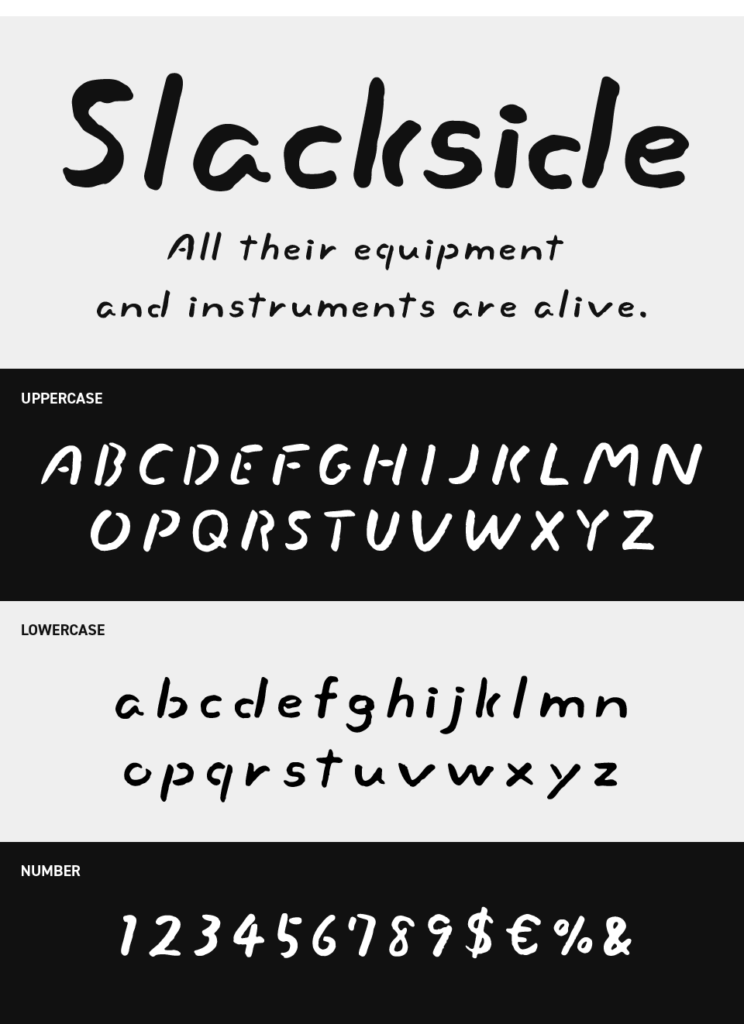
Slackside Font
Slacksideフォントは、ラフに書き留めたメモのような自然体の手書き感が魅力の手書きフォントです。
線の揺らぎや少し不揃いな字形が、整いすぎない親しみやすさを生み出しています。気取らず、会話するような空気感を伝えたいデザインにぴったりなフォントです。
力を抜いたカジュアルさがありながら読みやすく、日常に寄り添うやさしい雰囲気を演出できます。素直で人懐っこい表情を持つフォントです。